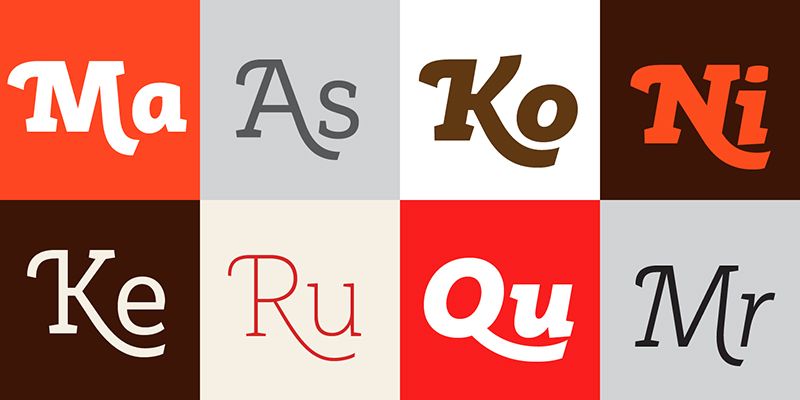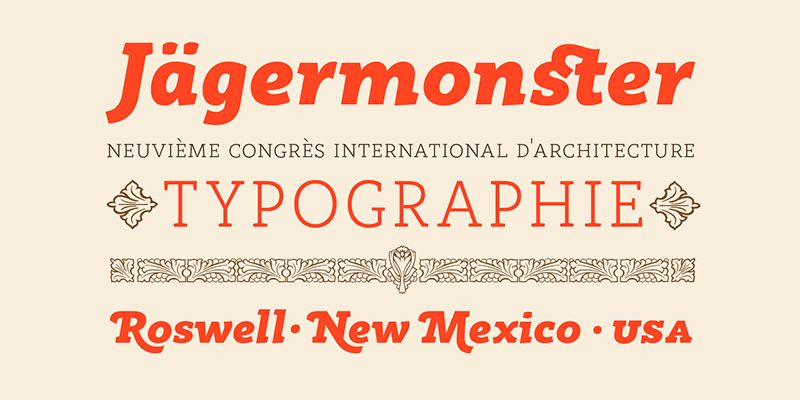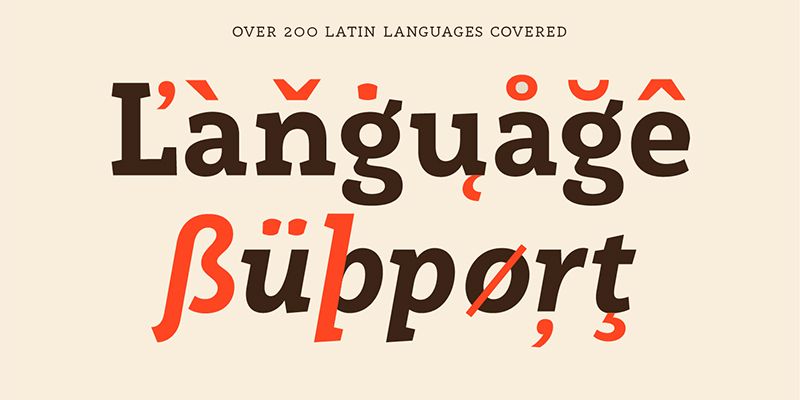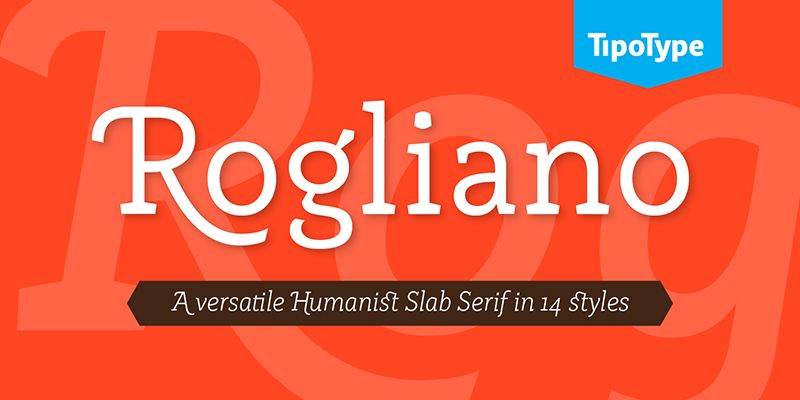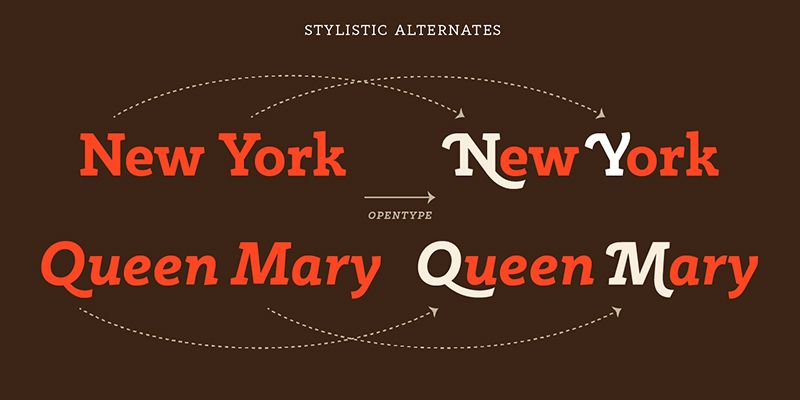
Rogliano risponde al classico principio degli alfabeti forti e diretti del periodo della Rivoluzione industriale. Mentre nutre il testo di un ambiente caldo, si prende la libertà di flirtare con scritte e poster litografici del periodo vittoriano.
Con OpenType è possibile trarre vantaggio da tutte le caratteristiche professionali dei nostri prodotti, come il maiuscoletto, i caratteri alternativi, i set stilistici e molti altri.